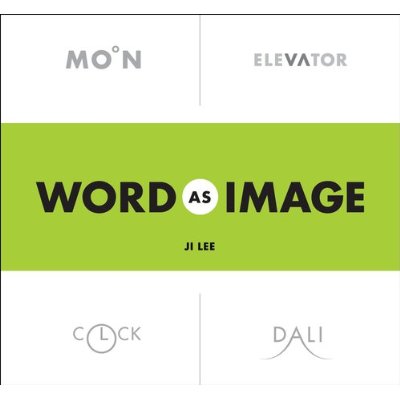
เมื่อ คำ+ภาพ รวมเป็นหนึ่ง
ทุกคนที่สนใจในการโฆษณาออนไลน์ ไม่ว่าจะเป็นคนทำงานกราฟฟิกหรือไม่ ก็ควรจะศึกษางานออกแบบเชิงพาณิชย์ไว้บ้าง และหนังสือใหม่ “Word as Image”ก็น่าสนใจทั้งโดยตัวผลงานในหนังสือเอง และทั้งตัวผู้เขียนด้วย
เจ้าของหนังสือก็คือ “Ji Lee” วัย 41 ปี ที่เดิมเป็น creative director ที่ฝ่าย Creative Labs ของ Google ก่อนที่จะถูกFacebook ดึงตัวไปเป็น creative director เมื่อเดือนเมษายน 2011 ที่ผ่านมา
Ji Lee ได้สร้างคลิปสั้นๆเพื่อโปรโมทหนังสือรวมงานดีไซน์เล่มนี้ เรียกว่าเป็น “animated taster” ที่โชว์การใช้ฟอนต์บวกเทคนิคภาพเคลื่อนไหว animation ช่วยสื่อความหมายของคำนั้นๆให้แรงให้ชัดและน่าสนใจขึ้นอีกมากมาย